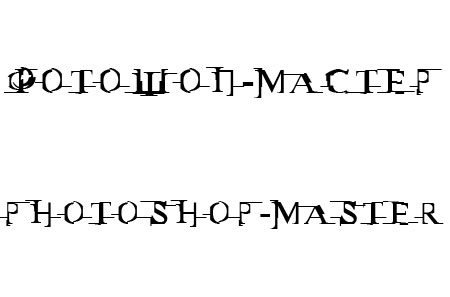
Дополнения Шрифты Татьяна Гапонова 8 июля 2009 Шрифт - matrix vs miltown Интересный шрифт с поддержкой русского языка. Скачать Шрифт - matrix vs miltown
циферки какие то кривые...
Великолепный Шрифт